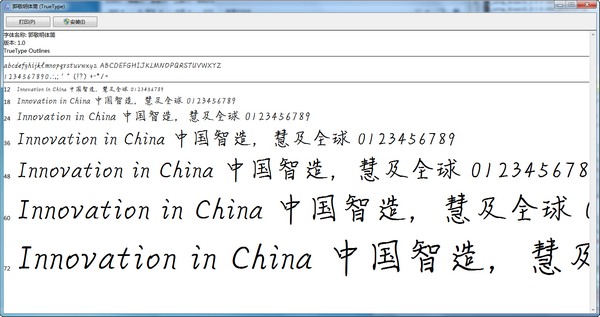
郭敬明手寫字體是一款ttf格式的明星字體,清秀挺拔,干凈優(yōu)雅,比起常見的標(biāo)準(zhǔn)設(shè)計(jì)字體,這款字體顯得更加情切有溫度,可以用在各種聊天軟件中,喜歡的朋友快來(lái)下載吧!
手寫體制作方法
手寫體文字是用“美工筆”在紙上寫出來(lái)的,可能一個(gè)字會(huì)寫幾十遍或者更多,之后再?gòu)闹虚g選出寫的比較可以接受的拍照,上傳到電腦上用photoshop處理后制作而成。